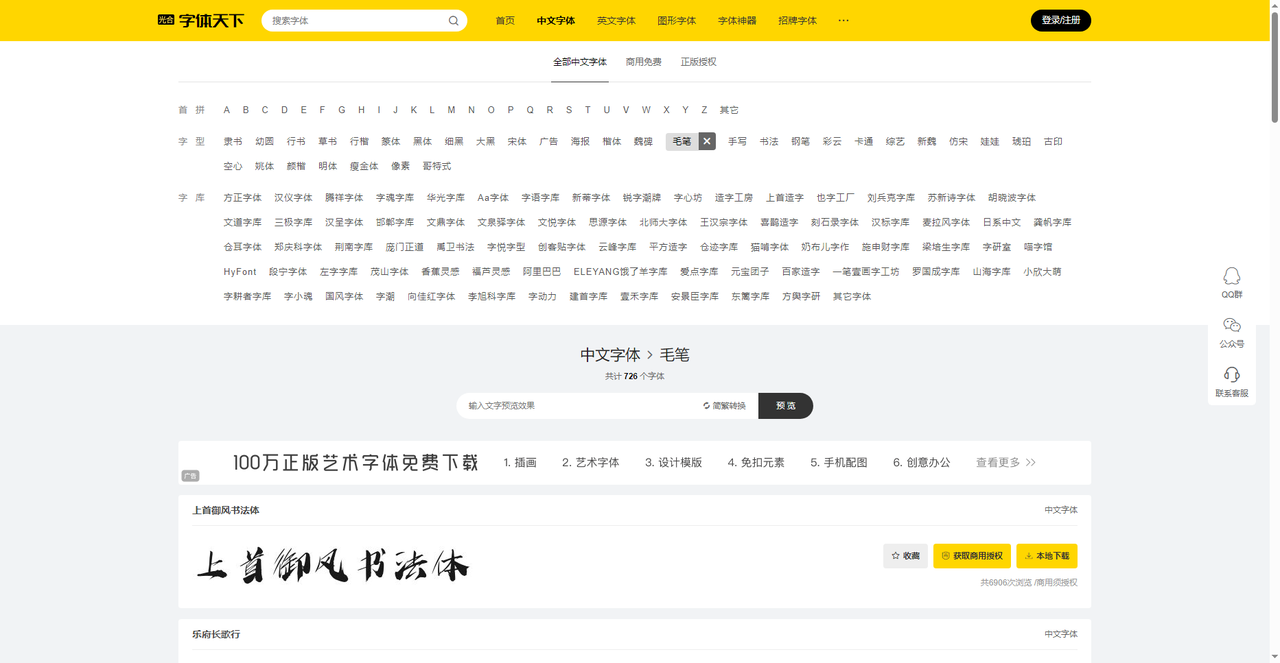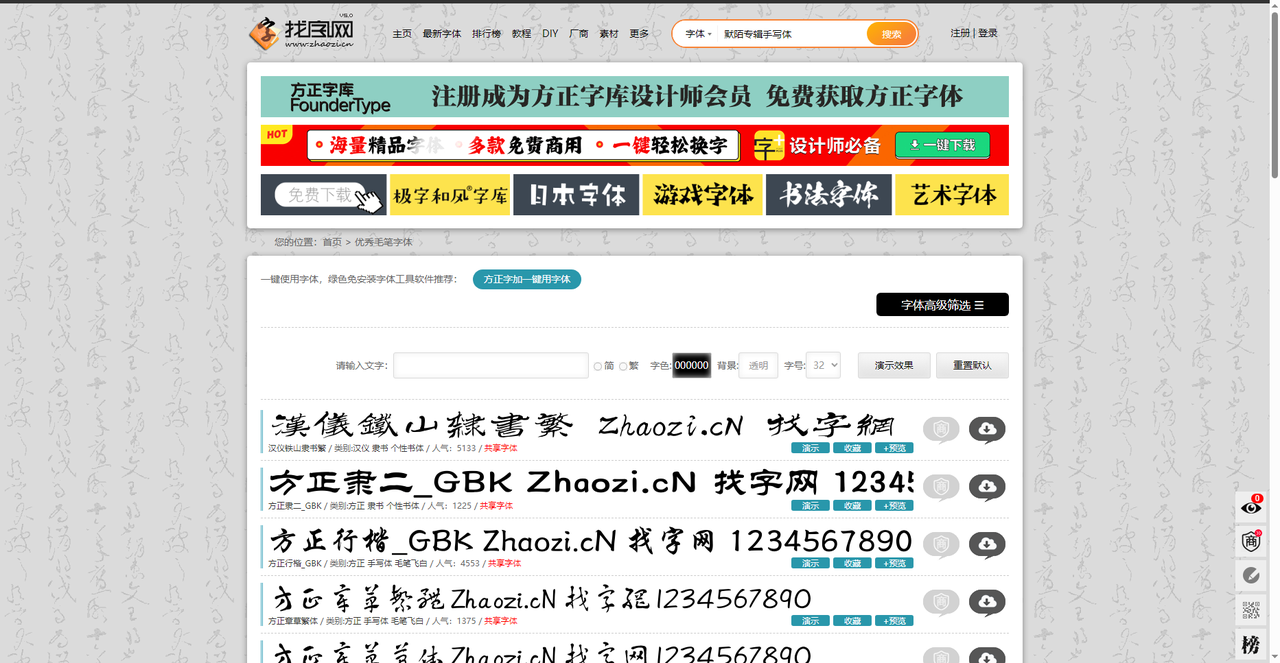
不用毛笔也能写出书法字:电脑毛笔字体资源推荐
毛笔书法是中国的传统艺术,行云流水、刚柔并济。做中式风格的海报、茶叶包装、品牌Logo、文化展板,用一款好看的毛笔字体,整个设计的气质就提上来了。但是没有自带的毛笔字体。怎么办?不用愁,网上有不少专门的毛笔字体资源站,你下载安装后,就和装普通字体一样,打出来就是毛笔效果。今天推荐5个靠谱的电脑毛笔字体下载渠道,有免费商用的,有正版授权的,有收录几百款的大平台,也有专业设计师必备的工具。按需选择即可。
字由是国内最大的字体管理与AI平台之一,它收录了大量正版毛笔字体,是专业设计师的首选。打开字由客户端或网页版,在筛选栏中可以选择“书法体”分类,或者直接搜索“毛笔”“行楷”“榜书”等关键词,就能找到丰富的毛笔字体资源。
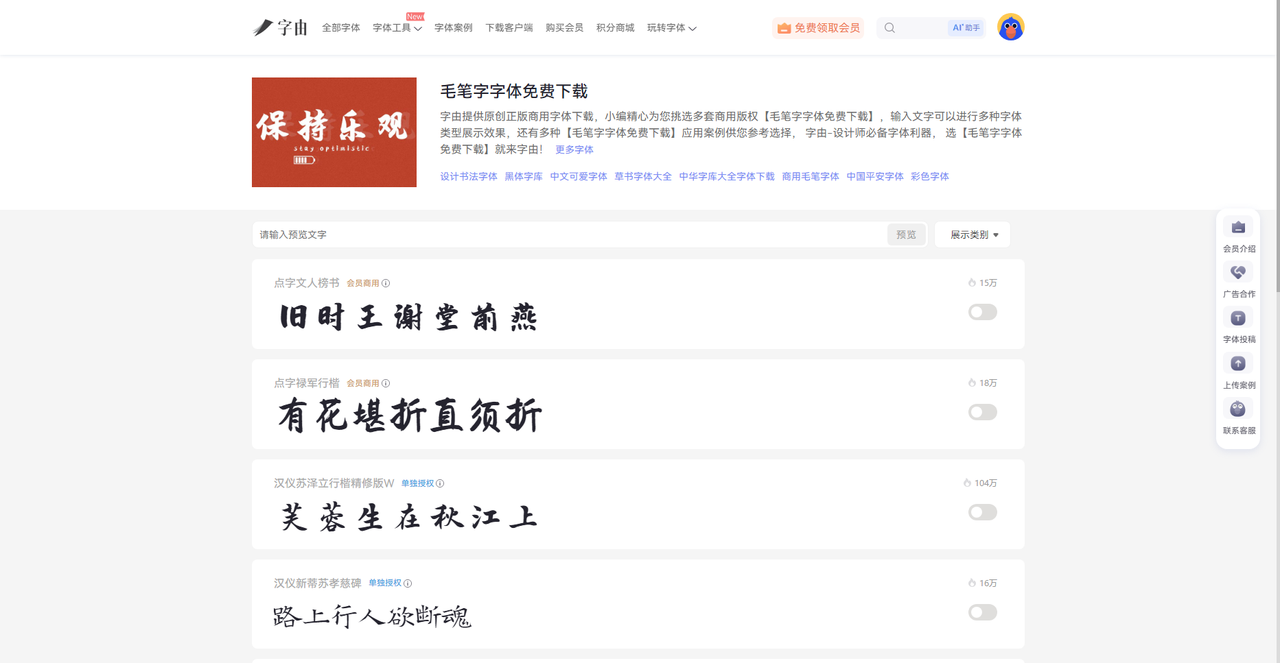
此外,字由还提供了更多毛笔字体如“汉仪黄科行书W”“汉仪瑞云袖舞”等。每款字体下方都有明确的热度数据,例如“演示悠然小楷”高达295万热度,说明被大量设计师验证过,品质可靠。授权类型分“会员商用”“单独授权”“免费商用”等,可以根据项目需求选择。
2、字体天下
第二个网站是字体天下。它收录了大量中文字体,其中毛笔字体单独作为一个大类。网站首页有明显的分类导航:隶书、幼圆、行书、草书、行楷、篆体、黑体、宋体……其中重点推荐的就是“毛笔”分类。页面显示“中文字体>毛笔,共计726个字体”,数量非常丰富。
3、找字网
第三个网站是找字网。它是一个字体聚合平台,提供多款毛笔字体的预览和下载。页面中的“字体高级筛选”功能可以设置预览文字、字号、背景透明等。展示的字体包括:
- 汉仪铁山隶书繁(类别:汉仪隶书,人气5133)
- 方正隶二_GBK(类别:方正隶书,人气1225)
- 方正行楷_GBK(类别:方正手写体/毛笔白,人气4553)
- 方正草篆繁体(类别:方正手写体/毛笔白,人气1375)
这些字体虽然部分标注为“隶书”或“行楷”,但都属于毛笔书法风格,适合传统设计。每款字体都有预览、收藏、演示功能。用户可以在线输入文字,实时看到毛笔字体的效果,满意后再点击下载。找字网的优点是字体品牌相对正规,方正、汉仪等大厂字体质量较高。不过有些字体可能标注为“共享字体”,商用需要仔细核对授权。对于个人学习和非商业项目,可以直接下载使用。它的界面简洁,上手容易,适合快速找到一款书法体并看到实际效果。
4、天空字体
第四个网站是天空字体。这个站点的风格比较复古,但内容很有特色。它专门整理了一系列书法字体,其中“毛笔字体”板块收录了“毛泽东”“段宁毛笔雅韵体”“衡山毛笔草书”等特色字体。天空字体还整合了大量书法资源,包括书法视频、书法家、篆刻、字库、五体书、古风、甲骨文等。它的字体总数显示为73634个,资源庞大。下载方式比较直接,点击字体链接即可获取。需要注意的是,这些字体的授权情况可能不够明确,商业使用前最好自行确认版权。如果你需要一些有特色的、不常见的毛笔字体,天空字体值得翻一翻。
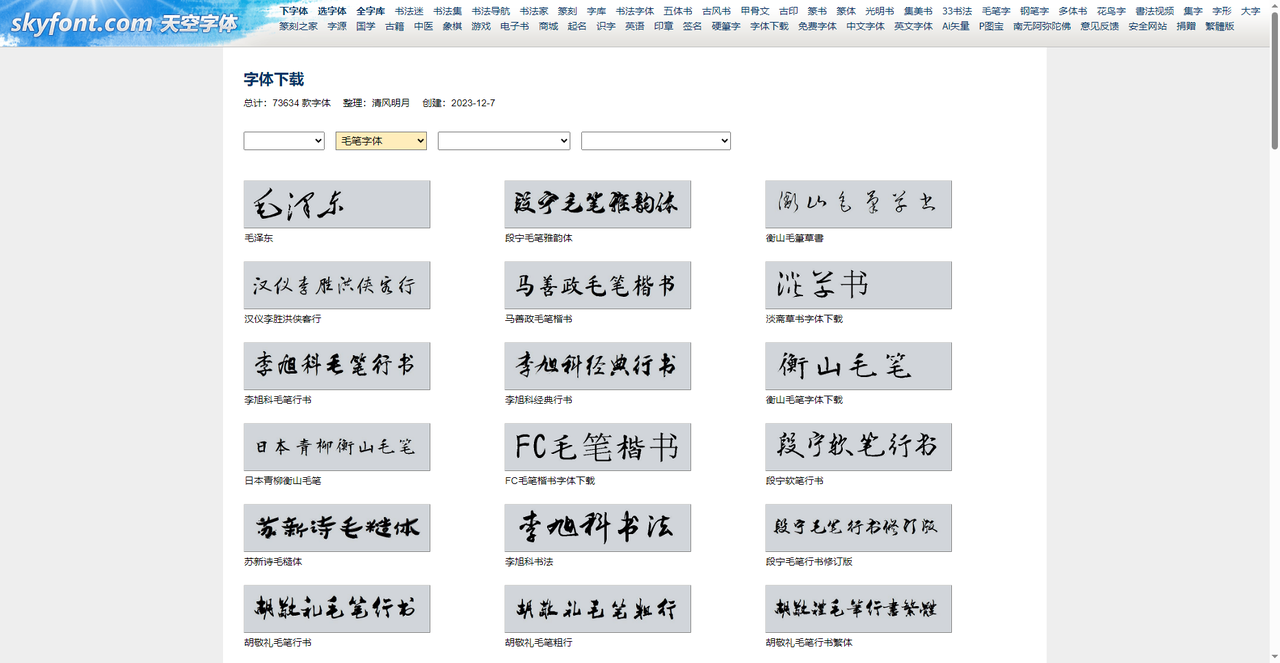
5、模板王
第五个网站是模板王。它的“毛笔字体下载”分类共收录240个毛笔字体。分类包括黑体、宋体、楷体、行书、草书、隶书、篆书、魏碑等,其中毛笔字体主要分布在“楷体”“行书”“草书”等子类下。
页面展示了多个也字工厂的毛笔字体,例如:
- 也字工厂春梅手书(风格柔美,适合女性化设计)
- 也字工厂浮生行楷(行楷笔意,潇洒自然)
- 也字工厂招牌体(粗重有力,适合牌匾)
此外还有“刻石录颜体”“Aa剑豪体”等。每款字体都有预览图片,点击下载按钮即可获取。模板王的字体大多由字体机构或设计师上传,授权情况各异。部分字体可能是免费个人使用,商用前需仔细查看。对于预算不足但需要大量毛笔字体做个人项目的用户,模板王是一个不错的资源站。
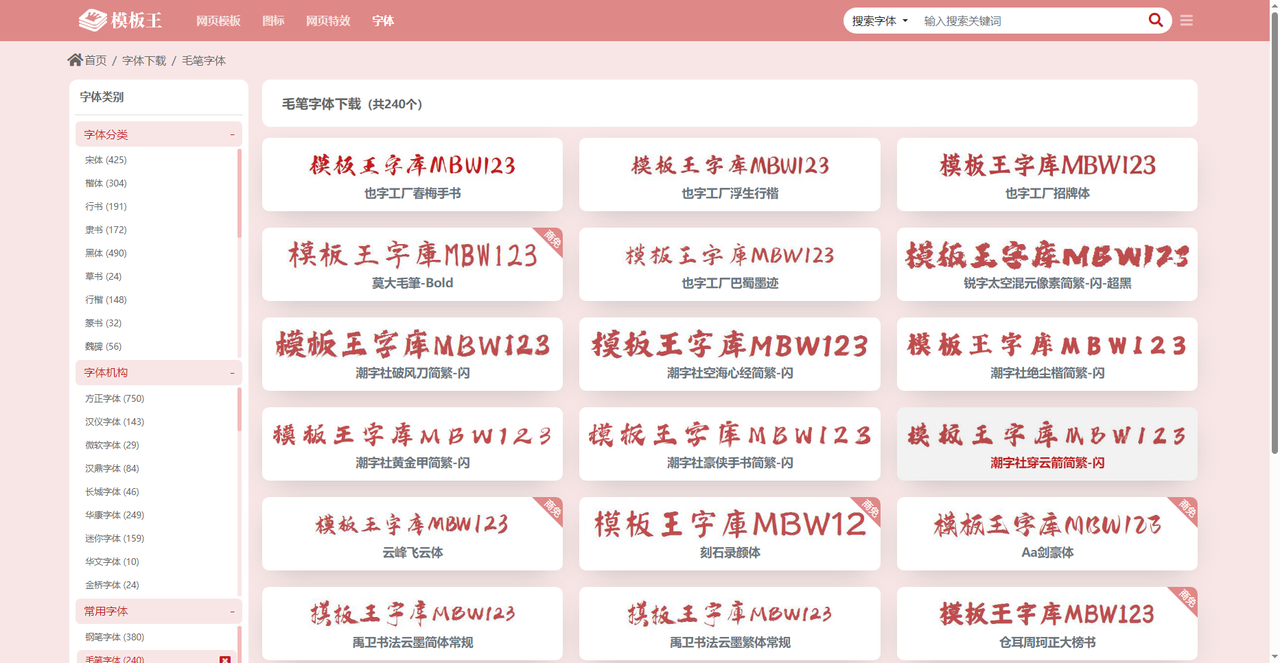
五款电脑毛笔字体下载渠道,各有侧重。字由最适合专业设计师,提供点字文人榜书、汉仪苏泽立行楷等正版毛笔字体,激活即用,云端同步,授权清晰;字体天下收录726个毛笔字体,数量最多,支持在线预览和本地下载,品牌全面;找字网提供方正、汉仪等大厂毛笔字体,支持预览筛选;天空字体有毛泽东、段宁毛笔雅韵体等特色字体,适合特定主题设计;模板王收录也字工厂系列等240个毛笔字体,资源丰富,下载方便。无论你是做品牌Logo、海报标题,还是个人创作,总有一个渠道能让你在电脑上打出有毛笔韵味的书法字。下载前建议确认字体授权,商业项目优先选免费商用或购买正版授权。